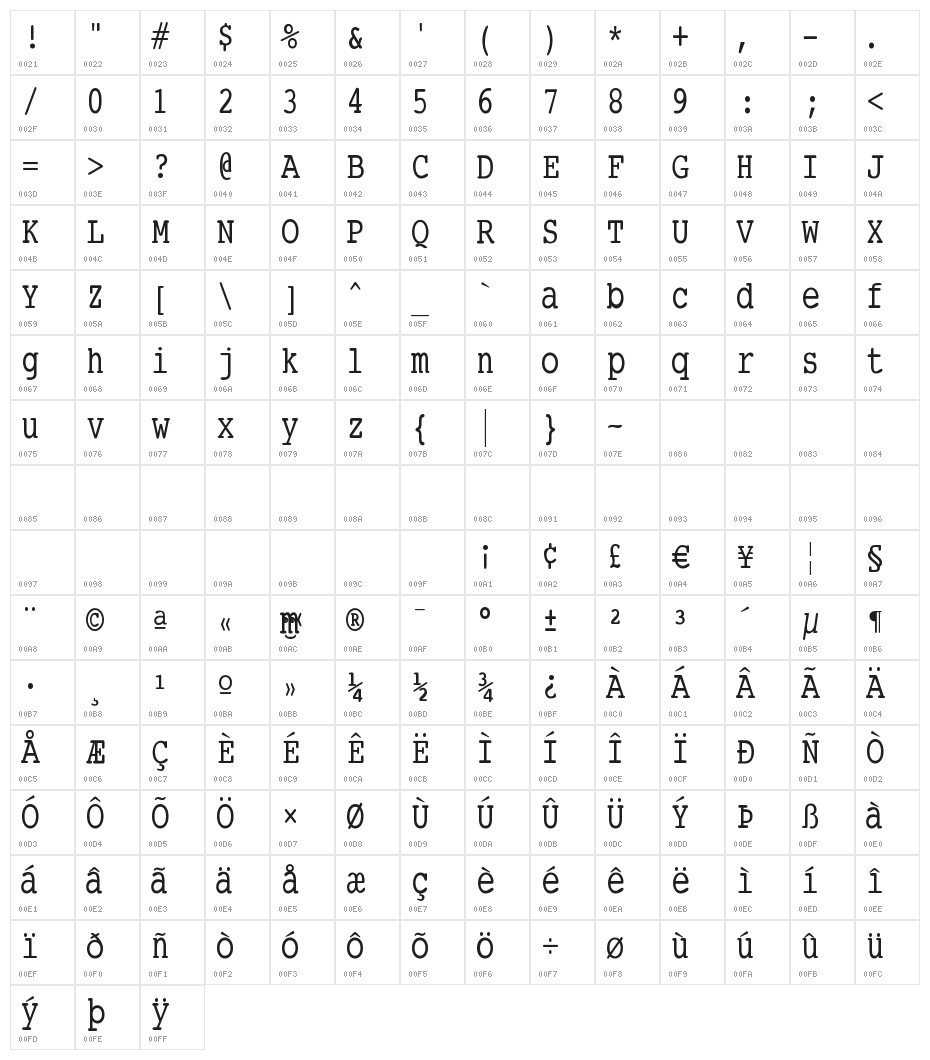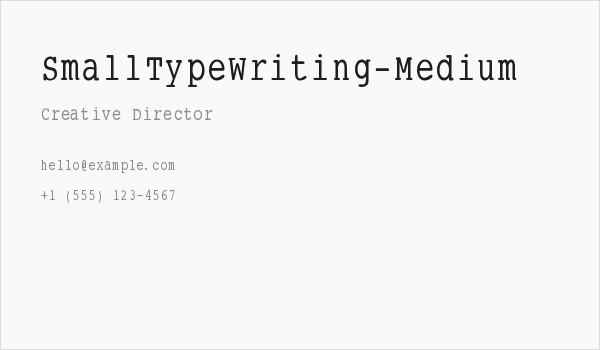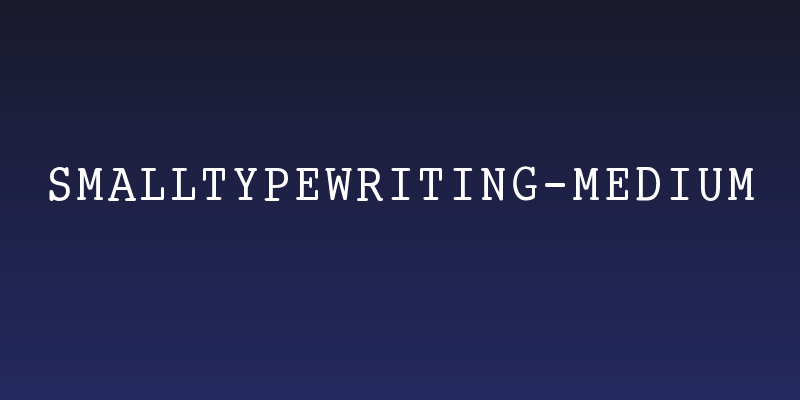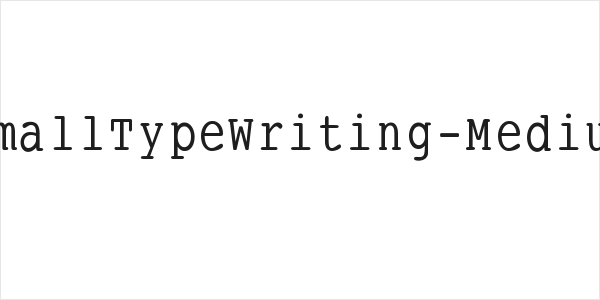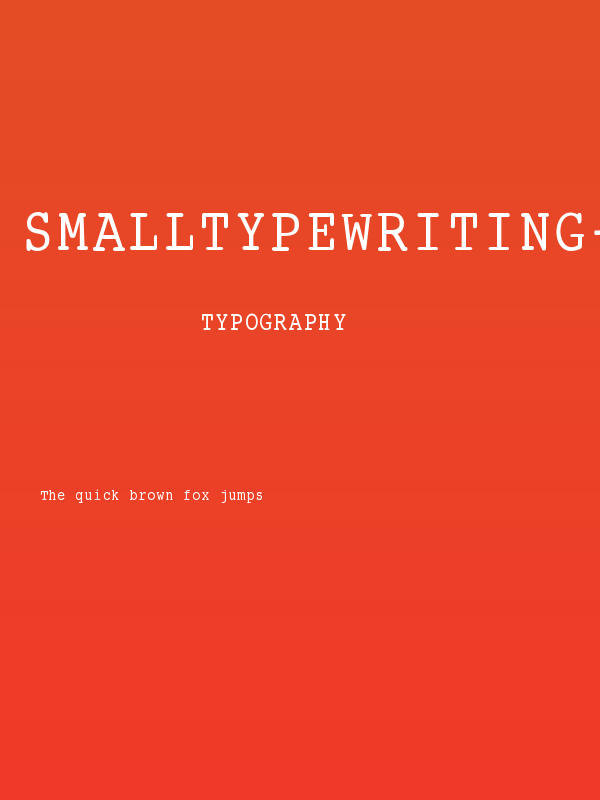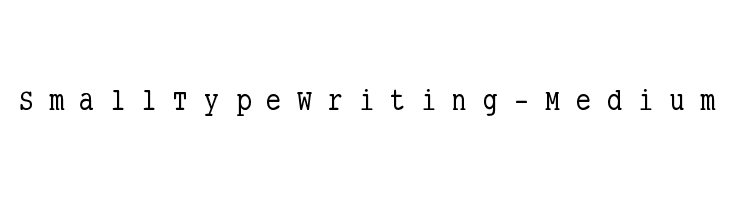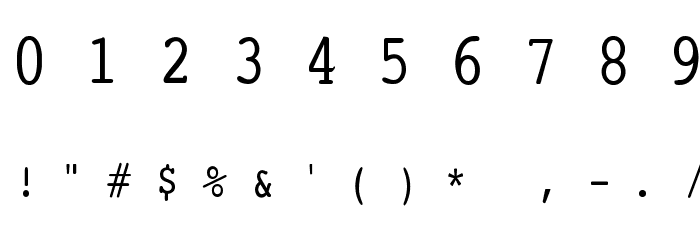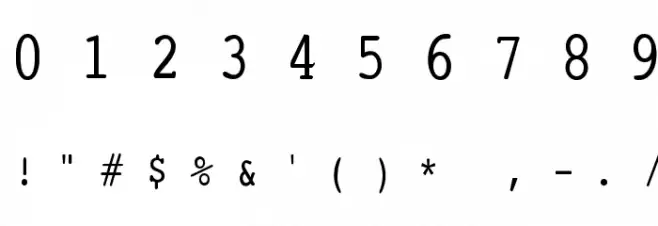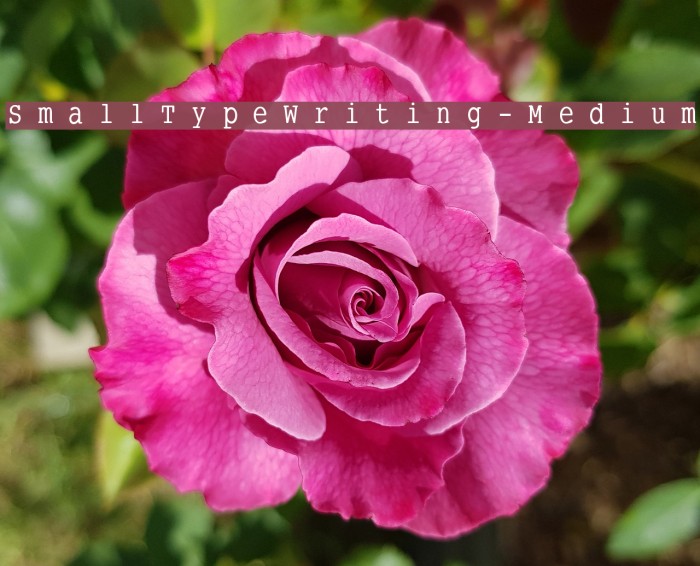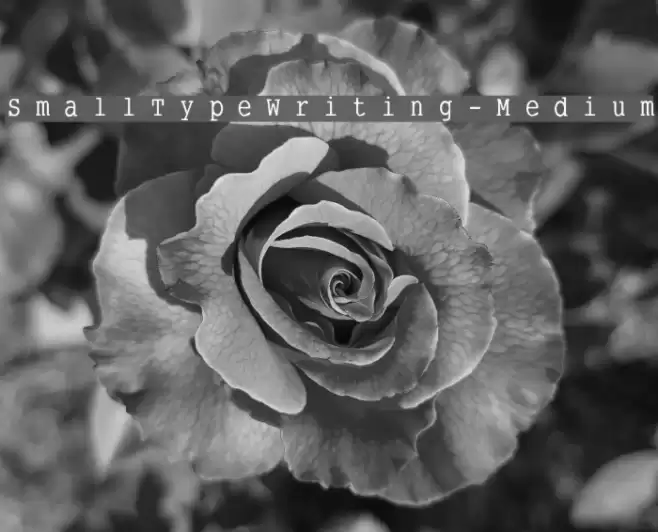
SmallTypeWriting-Medium Font
✎ Typewriter
| Caz de utilizare | Coding, Retro designs, Typewriter-themed projects |
| Proiecte propuse | Ideal for projects that require a retro or vintage aesthetic, such as typewriter-themed designs, coding environments, or any project that benefits from a monospaced font. |